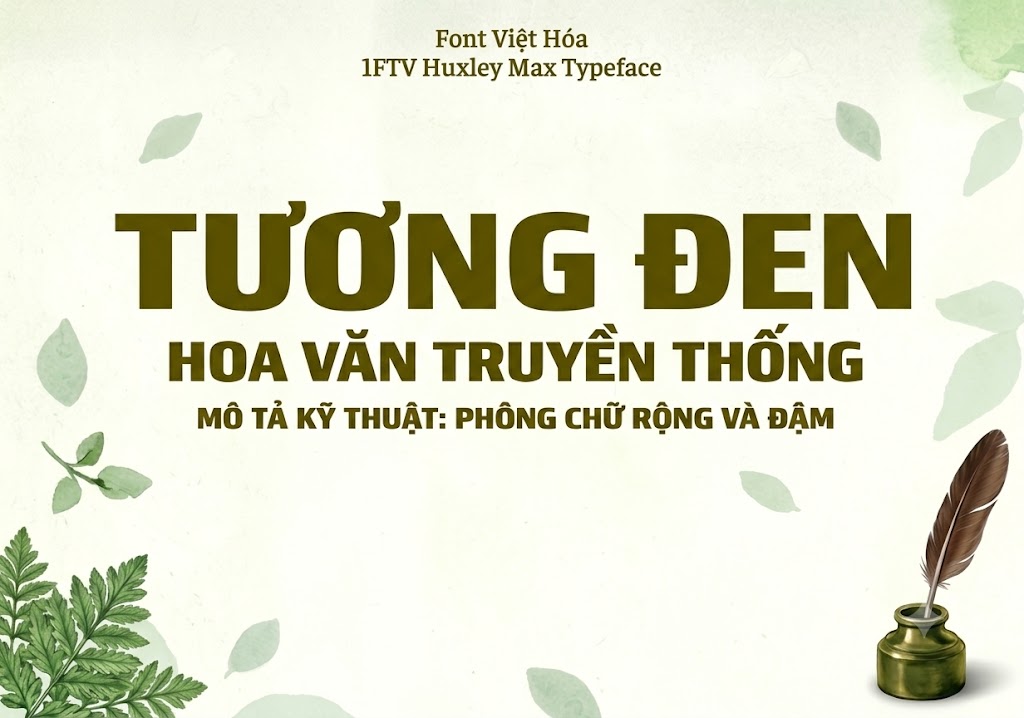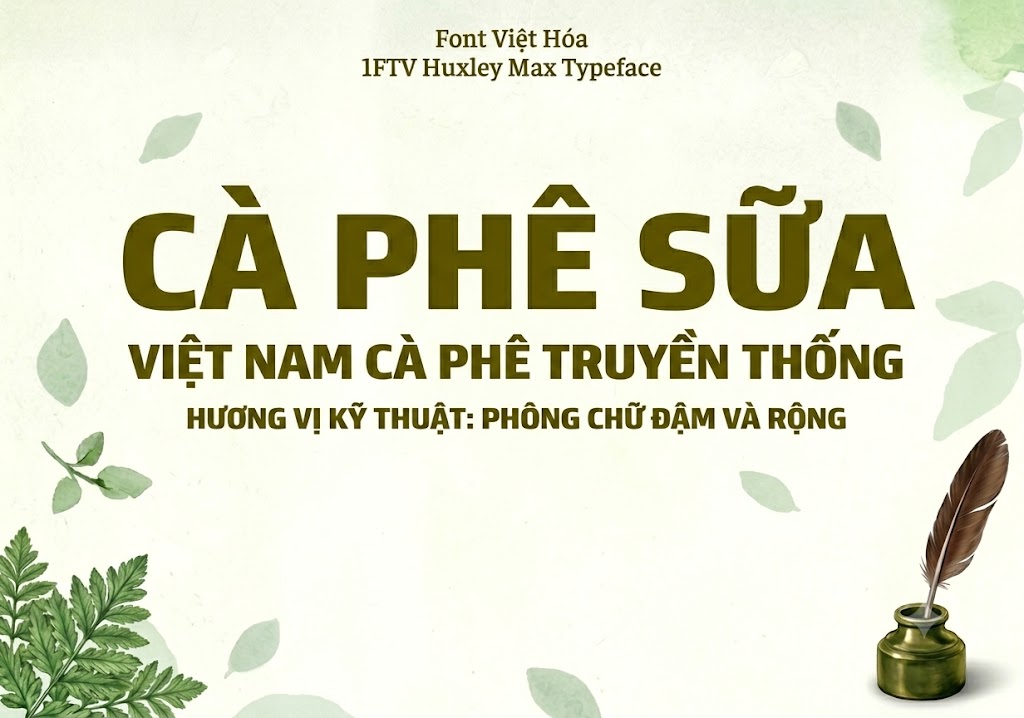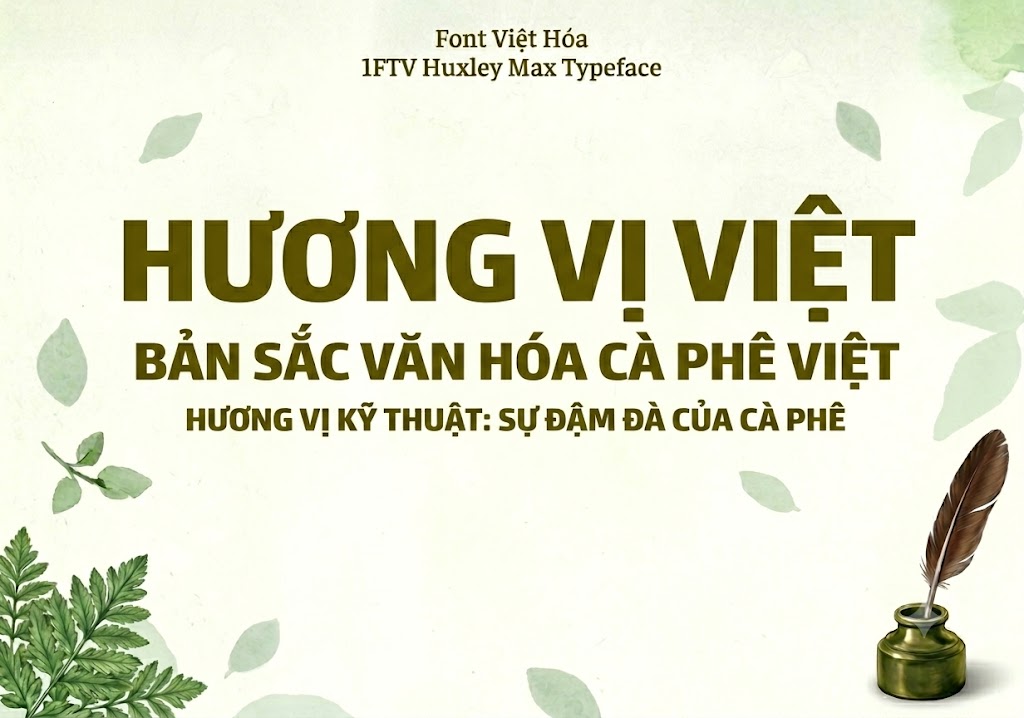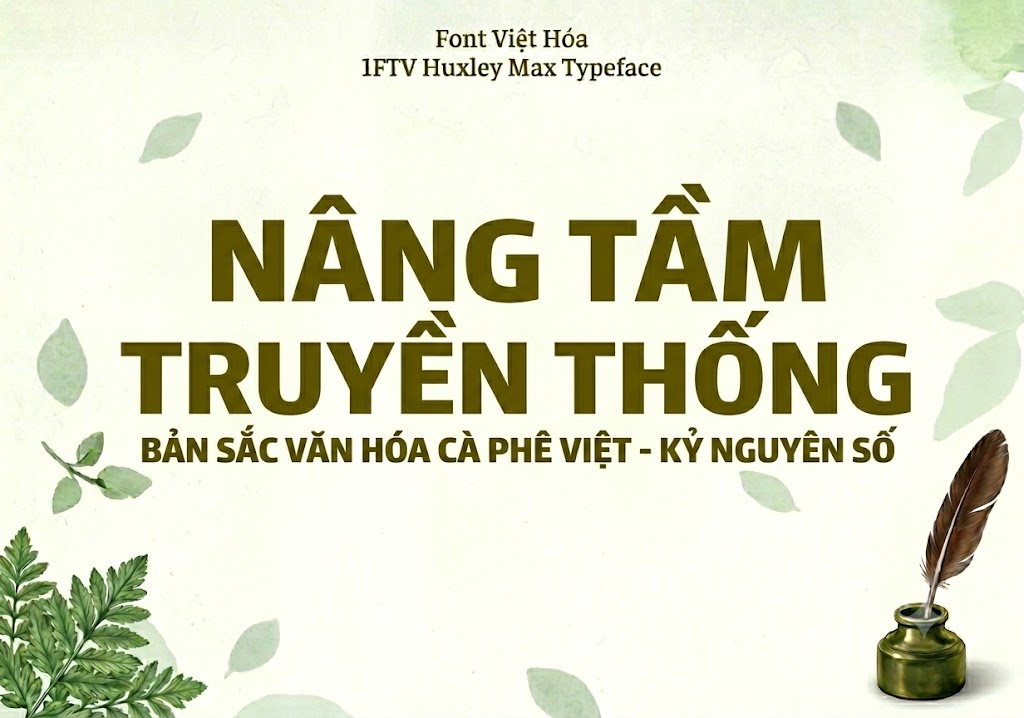
1FTV Huxley Max ExtBlk
Trong việc thiết kế bộ nhận diện thương hiệu hay sáng tạo nội dung số, các phông chữ thuộc nhóm Extra Black (siêu dày) luôn là sự lựa chọn hàng đầu để làm tiêu đề.
Tuy nhiên, phần lớn các font chữ siêu dày hiện nay thường chỉ hỗ trợ định dạng viết hoa toàn bộ, gây hạn chế khi bạn muốn thể hiện nội dung phân biệt chữ hoa chữ thường.
Nếu bạn đang tìm kiếm một giải pháp chữ khối đồ sộ, vững chãi nhưng vẫn có đầy đủ cả chữ thường lẫn chữ hoa để linh hoạt biến hóa, thì font 1FTV Huxley Max ExtBlk chính là câu trả lời hoàn hảo.
Giới thiệu về font 1FTV Huxley Max ExtBlk
Font 1FTV Huxley Max ExtBlk là một phông chữ hiển thị không chân mang phong cách hình học tối giản, thô ráp và đậm chất công nghiệp. Bộ font này được tối ưu hóa ở phiên bản 1.000, mang lại sự đồng bộ và mượt mà trong cấu trúc của từng con chữ.
Sản phẩm xuất hiện trong bài viết sở hữu định dạng opentype layout cao cấp, đi kèm chứng thực kỹ thuật số (digitally signed) và hệ thống đường nét dạng postscript outlines siêu chuẩn.
Nhờ các thông số kỹ thuật tối ưu này, phông chữ có khả năng hiển thị vô cùng sắc nét, hoàn toàn không bị răng cưa hay vỡ nét khi bạn phóng to hoặc thu nhỏ trên các phần mềm thiết kế đồ họa.
Được chia sẻ rộng rãi bởi đội ngũ 1FTV, đây là bộ font siêu dày có cả chữ thường hiếm hoi được cộng đồng designer Việt Nam đánh giá rất cao.
Đặc điểm nổi bật của phong cách thiết kế Huxley Max ExtBlk
Sức hút đặc biệt của font 1FTV Huxley Max ExtBlk đến từ cấu trúc “ExtBlk” (Extra Black) với các nét chữ siêu dày và vuông vắn.
Các chữ cái được hình khối hóa bằng những đường thẳng dứt khoát kết hợp bo góc nhẹ ở các cạnh ngoài. Điều này tạo cảm giác kiên cố như những khối bê tông nhưng không bị quá thô cứng.
Điểm bứt phá lớn nhất của bộ font này là việc hỗ trợ trọn vẹn cả hệ thống chữ thường (lowercase) bên cạnh bộ chữ viết hoa (uppercase).
Sự kết hợp này giúp dòng tiêu đề của bạn giữ được sự tự nhiên của ngôn ngữ. Từ đó tăng cường khả năng đọc hiểu nhanh mà vẫn duy trì được sức nặng thị giác đè lên các chi tiết nền phía sau.
Khoảng trống bên trong của các chữ cái được tính toán vô cùng khoa học, đảm bảo chữ không bị dính đặc lại khi hiển thị trên màn hình.
Để phông chữ vận hành mượt mà trên hệ thống máy tính và các phần mềm biên tập video hiện đại, phiên bản font 1FTV Huxley Max ExtBlk đã được xử lý kỹ lưỡng về mặt kỹ thuật số.
Hệ thống khoảng cách giữa các chữ (kerning) và độ giãn dòng (tracking) đã được căn chỉnh chuẩn xác. Việc này giúp các ký tự khi đứng cạnh nhau luôn giữ được sự liền mạch, hài hòa tuyệt đối.
Bên cạnh bộ chữ cái hoa và thường đồng bộ, phông chữ còn tích hợp đầy đủ dãy số từ 0-9 cùng hệ thống các ký tự đặc biệt, dấu câu thông dụng (.,;: ' " (!?) +-*/=).
Tiện ích này giúp bạn thoải mái sáng tạo nội dung đa dạng cho bài đăng hoặc video mà không lo bị lỗi font hay thiếu ký tự khi gõ.
Hình ảnh demo thực tế của font 1FTV Huxley Max ExtBlk
Để giúp bạn dễ dàng hình dung khả năng co giãn và hiển thị linh hoạt của phông chữ này trên các kích thước khác nhau, hãy cùng xem qua bảng mô phỏng thực tế:
Kích thước nhỏ (12pt – 24pt): Các nét chữ siêu dày và bộ chữ thường vẫn hiển thị rất rõ ràng, ngay ngắn, dễ đọc trên màn hình điện thoại di động.
Kích thước lớn (36pt – 72pt): Đây là không gian lý tưởng để font chữ phô diễn sức mạnh hình khối đồ sộ của mình, tạo hiệu ứng thị giác đè nặng cực mạnh cho các tiêu đề chính.
Ứng dụng của font Huxley Max ExtBlk trong thiết kế đồ họa và làm video
Nhờ sở hữu nét cá tính bứt phá và cấu trúc hoa – thường linh hoạt, font 1FTV Huxley Max ExtBlk mở ra không gian ứng dụng rộng lớn cho các dự án marketing và truyền thông:
Thiết kế thumbnail Youtube và ảnh thu nhỏ mạng xã hội: Đây là vũ khí hạng nặng để tăng tỷ lệ nhấp chuột (CTR). Khi kết hợp các khối chữ viết chữ thường xen lẫn chữ hoa với tông màu nổi bật như vàng, trắng trên nền tối, dòng tiêu đề sẽ lập tức đập vào mắt người xem.
Làm tiêu đề video ngắn (Tiktok, Shorts, Reels): Rất thích hợp để làm các cụm từ từ khóa chính, tiêu đề mở đầu video phong cách mạnh mẽ, giúp giữ chân người xem lướt chậm lại để theo dõi.
Banner và poster quảng cáo ngành công nghiệp, thể thao: Hoàn hảo cho các poster giải đấu thể thao, banner câu lạc bộ gym, xe độ, đồ gia dụng nặng hoặc các ngành công nghiệp đòi hỏi tính cơ bắp, chắc chắn và bền bỉ.
Nhận diện thương hiệu thời trang streetwear: Phù hợp làm logo dạng chữ khối, artwork in lên áo phông, áo hoodie cho các thương hiệu thời trang mang phong cách đường phố, bụi bặm và phá cách.